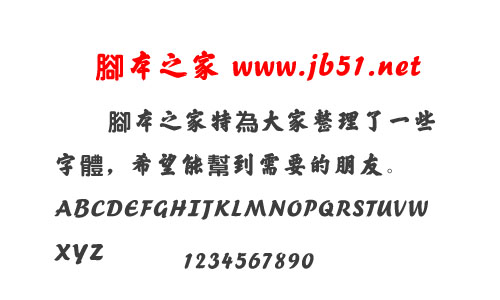
方正榜書行繁體字體(FZBangShuXingT-R-GB.ttf)是一款由方正字庫推出的手寫風(fēng)格的中文藝術(shù)字體,該字體設(shè)計源于明、清兩朝宮闕匾額、楹聯(lián)上的行楷大字,將傳統(tǒng)書法與現(xiàn)代字體設(shè)計相融合,保留了毛筆書寫的筆觸,増加了飛白處理,筆形追求筆墨的情趣,做到古為今用,能夠適用于藝術(shù)設(shè)計、包裝印刷、簽名設(shè)計、圖形設(shè)計等領(lǐng)域,歡迎有需要的朋友前來下載使用。
方正榜書行繁體字體詳細(xì)介紹:
榜書行體的設(shè)計靈感來源于明、清兩朝科舉匾額、楹聯(lián)上的行楷書的大字。 榜書為歷代書家所推崇,古人形容榜書:筆墨雍容,氣韻中正,雄健磅礴,自古為難。方正榜書行體將傳統(tǒng)書法與現(xiàn)代字體設(shè)計相融合,保留了毛筆書寫的筆觸,増加了飛白處理,追求筆墨的情趣,做到古為今用,使字體氣韻更加靈動,充滿活力。